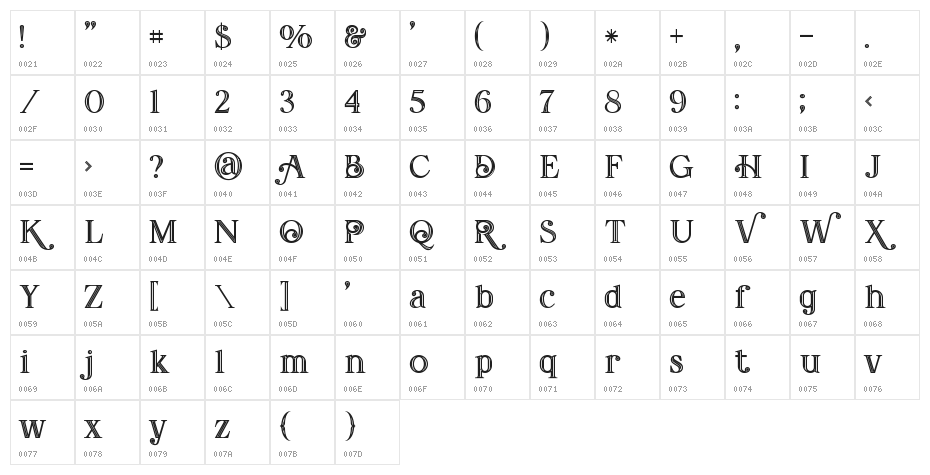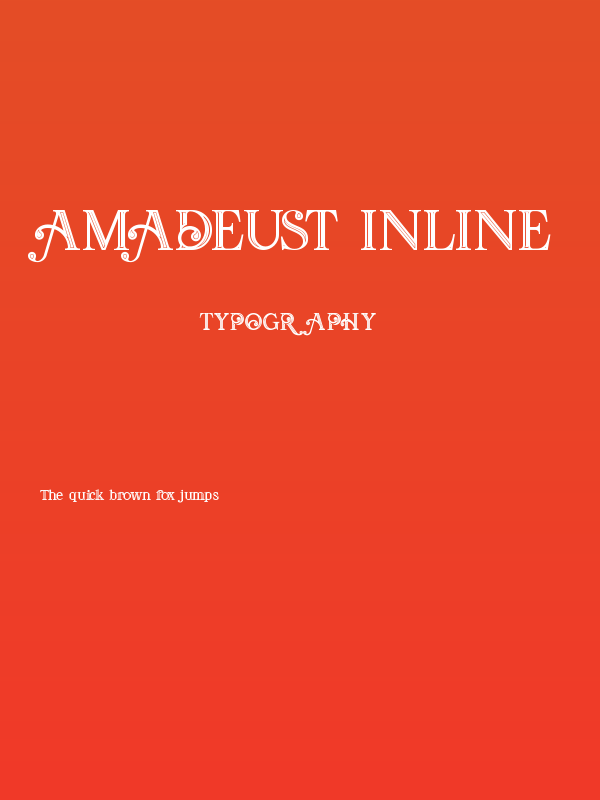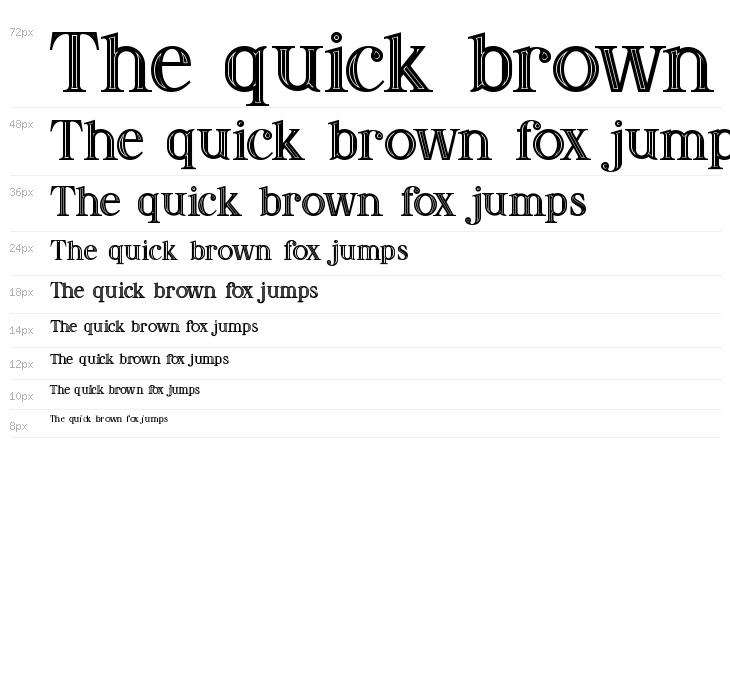
Amadeust Inline Font
✎ Curly
| Categorie | Curly |
| Caso d'uso | Headlines, Logos, Invitations |
| Progetti proposti | Ideal for wedding invitations, luxury branding, high-end product packaging, and decorative headlines. |